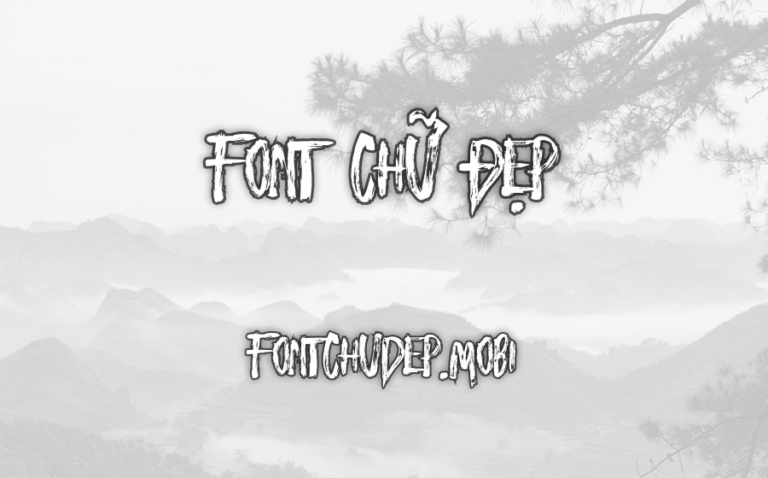
Font SVN Karasha Việt Hóa
Tôi vừa có dịp trải nghiệm font chữ Karasha phiên bản Việt hóa, một sản phẩm từ STYLEno.1 Fonts, được gọi là Font SVN Karasha. Đây thực sự là một font chữ đầy ấn tượng với phong cách mang đậm nét Nhật Bản và chất Á Đông, rất phù hợp với những dự án cần […]